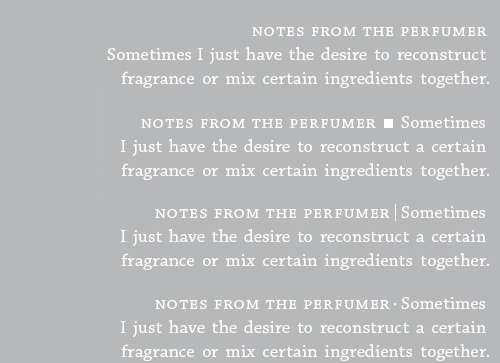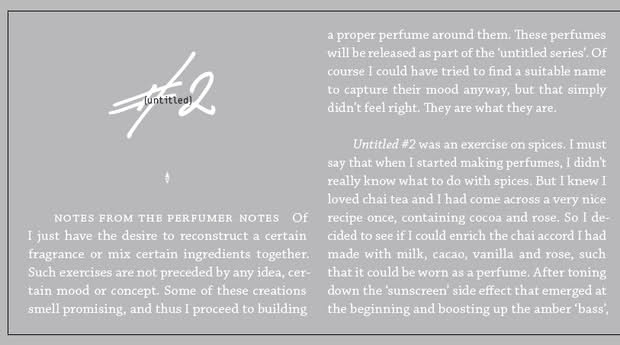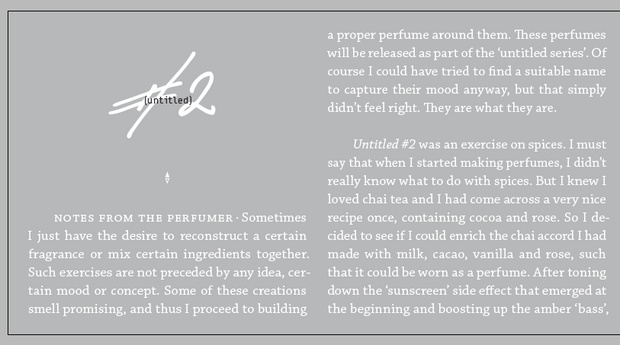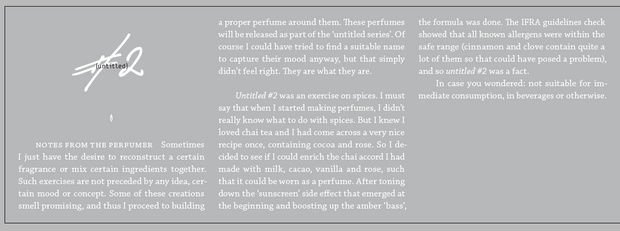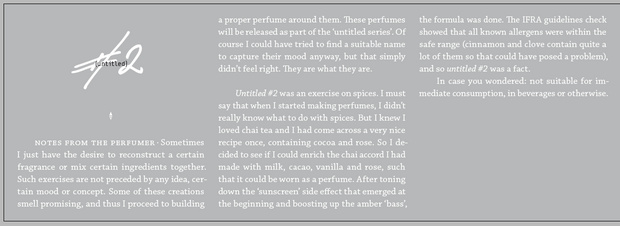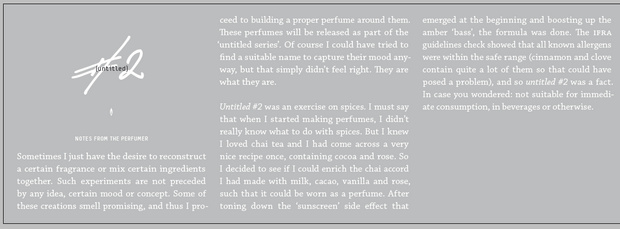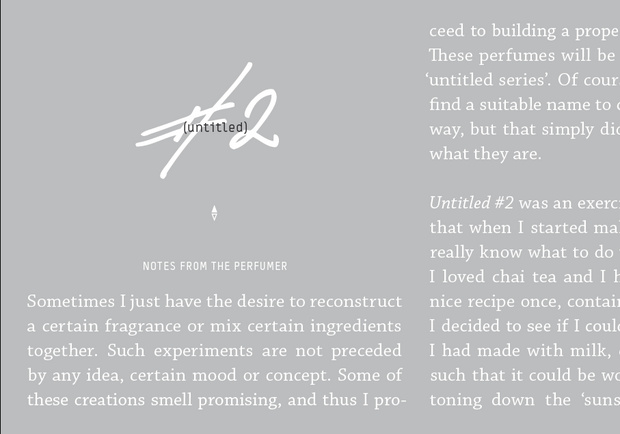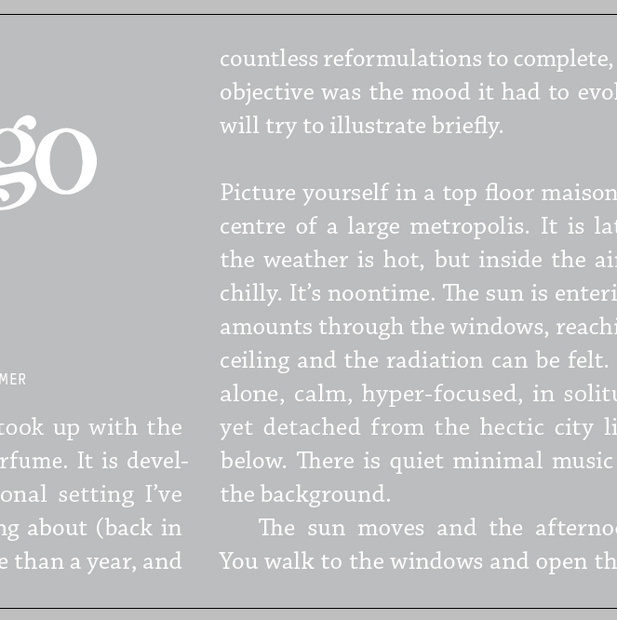
[Mitglied Matt…] Geschrieben März 14, 2012 Teilen Geschrieben März 14, 2012 Schönen guten Tag. Ich habe ein kleines (?) typografisches Problem für das ich keine Lösung finde. Es geht um folgende Textpassage: NOTES FROM THE PERFUMER · Sometimes I just have the desire to reconstruct ... Hier ein Bild dazu. Frage: Mit welchem Zeichen vollziehe ich die Abtrennung? Einen Doppelpunkt möchte ich nicht verwenden, da ich sonst klein weiterschreiben müsste (engl. Variante mit Kleinschreibung nach Doppelpunkt). Ist der Punkt eine legitime Möglichkeit? Vielen Dank Sebastian Link zu diesem Kommentar
[Mitglied 8dac…] Geschrieben März 14, 2012 Teilen Geschrieben März 14, 2012 Warum nicht als Überschrift ansehen und nach dieser einen Zeilenumbruch? Link zu diesem Kommentar
[Mitglied 8dac…] Geschrieben März 14, 2012 Teilen Geschrieben März 14, 2012 Oder einfach ein anderes Zeichen? Link zu diesem Kommentar
[Mitglied Kath…] Geschrieben März 14, 2012 Teilen Geschrieben März 14, 2012 Ich finde den hochgesetzten Punkt als Trennzeichen sehr schön. Die Frage ist nur, ob er im Kontext englischer Typografie auch auf diese Weise angewendet werden darf, da kenne ich mich leider nicht aus. Link zu diesem Kommentar
[Mitglied 8dac…] Geschrieben März 14, 2012 Teilen Geschrieben März 14, 2012 Schön finde ich ihn grundsätzlich auch. Nur finde ich das Layout im konkreten Fall sehr ungünstig, da ein einzelnes Wort des Fließtexts folgt – bei einem etwas längeren Intro-Satz würde gar kein Fließtext in der selben Zeile folgen. Da fände ich die klare Trennung mit Umbruch am logischsten. Link zu diesem Kommentar
[Mitglied Kath…] Geschrieben März 14, 2012 Teilen Geschrieben März 14, 2012 Da hast Du recht. Aber wir wissen natürlich nicht, wie das übrigen Dokument aussieht. Wenn da alle Absätze so beginnen, dann kann man ja schlecht bei einem einzelnen Absatz plötzlich einen Umbruch einfügen. Link zu diesem Kommentar
[Mitglied Matt…] Geschrieben März 14, 2012 Themen-Ersteller Teilen Geschrieben März 14, 2012 Vielen Dank für eure Ideen und Gedanken. Genau das war das Dilemma. Einen Umbruch konnten wir aus optischen gründen nicht setzen. Erst hatte ich ein Semikolon gesetzt, aber das war wohl wirklich falsch. Mir schien der Punkt die dezenteste Abgrenzung, ohne mit dem glyphischen Vorschlaghammer zu kommen. Ich hab mal mehr Text an Screenshot vorbereitet, damit ihr eine besseres Bild bekommt. Und was ich noch erwähnten sollte ist: es gibt mehrere Verschiedene Texte (entsprechend Düfte), immer mit dem Vorangestellten Vermark beginnen und danach aber unterschiedlich weiterlaufen. Link zu diesem Kommentar
[Mitglied Thie…] Geschrieben März 14, 2012 Teilen Geschrieben März 14, 2012 ich schlage als trenner vor: drei oder vier leerzeichen mit fester breite. sollte die ›überschrift‹ doch mal die ganze erste zeile füllen, fallen die leerzeichen eben weg. außerdem würde ich am absatzbeginn nicht einrücken. ihr habt doch schon abstände zwischen den absätzen. eines von beidem – abstände oder einrückung – ist in der regel genug. sonst gefällt mir euer layout aber gut. das ist die chaparral, oder? Link zu diesem Kommentar
[Mitglied Diet…] Geschrieben März 14, 2012 Teilen Geschrieben März 14, 2012 Ich finde, dass man hier überhaupt kein weiteres Zeichen außer dem Leerzeichen benötigt, die Differenzierung durch die Versalien genügt. Link zu diesem Kommentar
[Mitglied 8dac…] Geschrieben März 14, 2012 Teilen Geschrieben März 14, 2012 Ich finde, das man hier überhaupt kein weiteres Zeichen außer dem Leerzeichen benötigt, die Differenzierung durch die Versalien genügt. Das würde ich als die schlechteste aller Lösungen ansehen. Link zu diesem Kommentar
[Mitglied R::b…] Geschrieben März 14, 2012 Teilen Geschrieben März 14, 2012 Mir erscheint der Ansatz von ThierryM sowohl elegant als auch praktikabel. Wie Dieter fände ich den Leerraum auch völlig ausreichend. Um die Sinn-Einheiten besser als solche wahr zu nehmen würde ich aber unbedingt einen Geviert-Leerraum wählen. Nur ein normales Leerzeichen wäre mir auch zu wenig. Link zu diesem Kommentar
[Mitglied 8dac…] Geschrieben März 14, 2012 Teilen Geschrieben März 14, 2012 Das sähe dann im schlimmsten Fall so aus: "Elegant" und "praktikabel" sähen bei mir anders aus. Link zu diesem Kommentar
[Mitglied R::b…] Geschrieben März 14, 2012 Teilen Geschrieben März 14, 2012 Na das hast Du Dir jetzt aber wieder schön zurecht getrickst! : ) Aber Du hast natürlich Recht. Hier würde es aber ein Trennzeichen wie der hochgerückte Punkt auch nicht mehr raus reißen, oder? Thierry meinte, den ersten Absatz nicht einzurücken. Aber in diesem Fall würde das Ergebnis auch nicht spürbar besser ausfallen. Und wenn wir doch noch mal Deine Überschrift-Idee aufgreifen und mit zwei Absatzlinien (darüber und darunter) arbeiten um den Block optisch zu erhalten? Das würde aber je eine Leerzeile Platzverlust bedeuten. Link zu diesem Kommentar
[Mitglied Thie…] Geschrieben März 14, 2012 Teilen Geschrieben März 14, 2012 "Elegant" und "praktikabel" sähen bei mir anders aus. wie sähe es denn mit einem mittelpunkt aus, wenn der vorspann so lang ist, dass er die komplette erste zeile füllt? fällt der punkt dann weg, weil der zeilenumbruch als trenner genügt, oder bleibt er am zeilenende stehen? ersteres wäre inkonsistent, letzteres vermutlich hässlich. und wenn man nach dem vorspann einen zeilenumbruch setzt: was passiert, falls noch ein wörtchen des vorspanns in eine zweite zeile hinüberragt? da erscheinen mir sowohl der mittelpunkt als auch ein fester leerraum praktikabler. außerdem fehlt der variante mit obligatorischem zeilenumbruch meines erachtens der reiz, dass eine typografisch abgesetzte ›spitzmarke‹ direkt an den haupttext anschließt. die entscheidung, welche variante das problem löst, lässt sich wohl nur anhand der konkreten texte treffen. vielleicht kann mattskar sie alle einmal durchprobieren und berichten, welche ihm am besten gefallen hat. mein favorit ist weiter der feste leerraum mit einer breite von drei oder vier leerzeichen. Link zu diesem Kommentar
[Mitglied 8dac…] Geschrieben März 14, 2012 Teilen Geschrieben März 14, 2012 die entscheidung, welche variante das problem löst, lässt sich wohl nur anhand der konkreten texte treffen. Darin sind wir uns wahrscheinlich alle einig Link zu diesem Kommentar
[Mitglied Matt…] Geschrieben März 15, 2012 Themen-Ersteller Teilen Geschrieben März 15, 2012 ich hab zwei schriften. die zweite schrift wird nur in den schriftgrößen 5,5 und 7pt auf dem dokument verwendet. da 7pt zu groß war und ich keine neue schriftgröße einführen wollte, viel die entscheidung auf 5,5pt. ist auch für die information ausreichend. super. dann kann's jetzt in den druck und in einem monat ist es dann im Handel erhältlich, oder hier: www.magnetic-scent.com Link zu diesem Kommentar